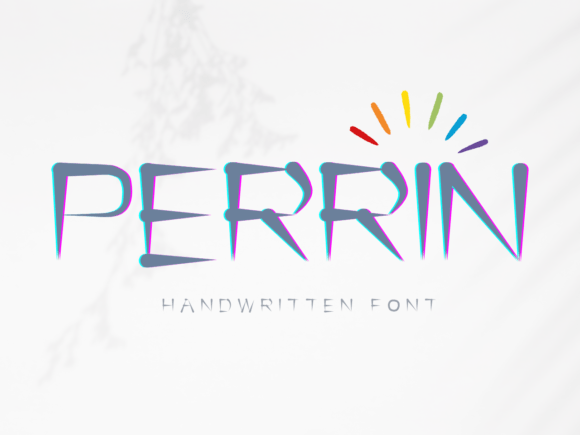
Perrin
Việc tìm kiếm các thành phần thiết kế phù hợp có thể là một thách thức, nhưng Perrin cung cấp một bộ sưu tập đặc biệt giúp nâng tầm công việc của bạn ngay lập tức.
Cho dù bạn đang tạo sản phẩm POD (In theo yêu cầu), thiệp mời đám cưới hay đồ họa mạng xã hội, Perrin đều là một sự lựa chọn lý tưởng.